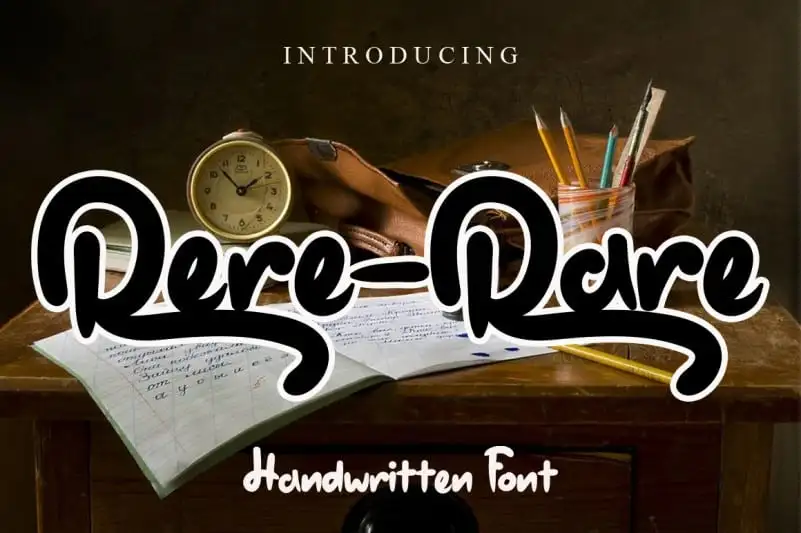
Rere Rare Font – Download Grátis
A Rere Rare Font é uma fonte à mão escrita simples, fina e docemente pintada. Esta é uma tipografia versátil que se adapta a uma variedade de designs, elevando-os ao nível mais alto. Pode ser usada para gráficos como ologramas, flyers ou até mesmo para criar um toque nostálgico em design de sites e aplicativos. A Rere Rare Font é perfeita para quem busca uma fonte elegante e delicada que se encaixa bem em diferentes ambientes digitais. É perfeito para designers buscando aquele charme único que torna seus projetos ainda mais especializados.